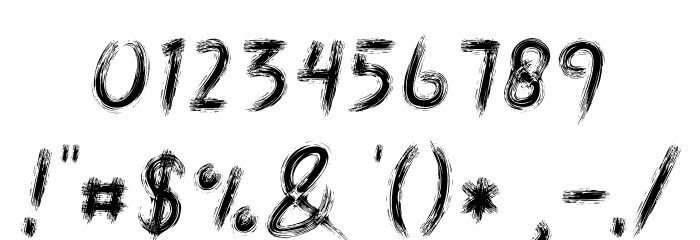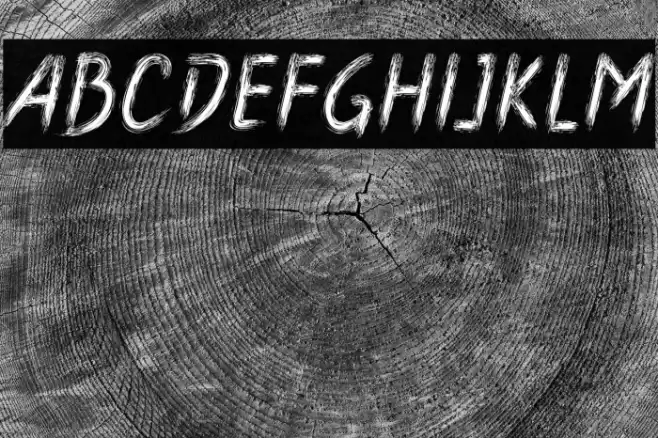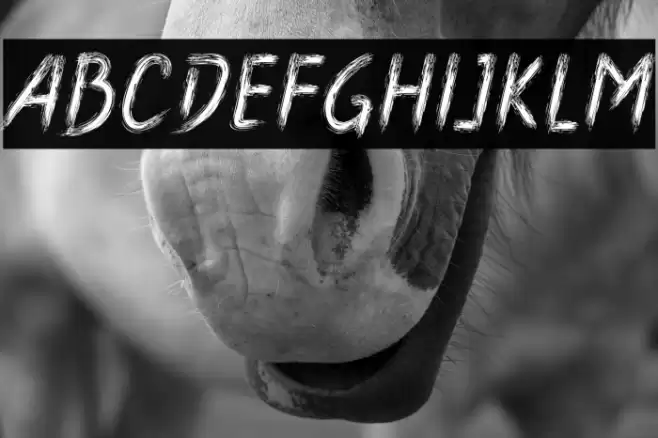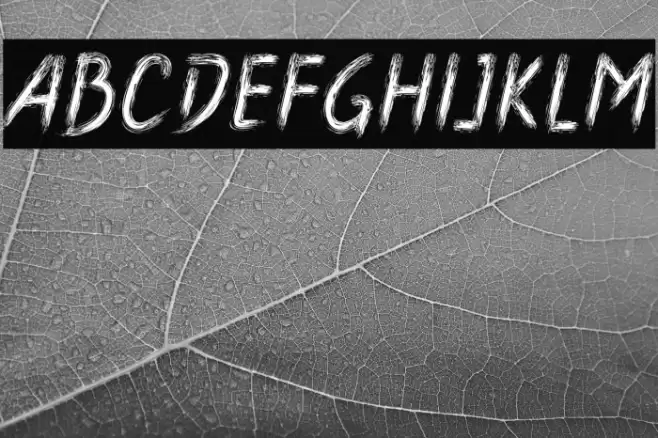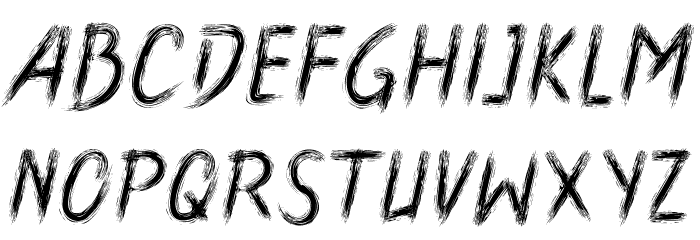
Boldace Brush Font
✎ Messy
| Categorie | Messy |
| Stile generale | Modern, Artistic |
| Progetti proposti | Ideal for posters, branding, social media graphics, and artistic projects that require a bold, expressive typeface. |
Boldace Brush